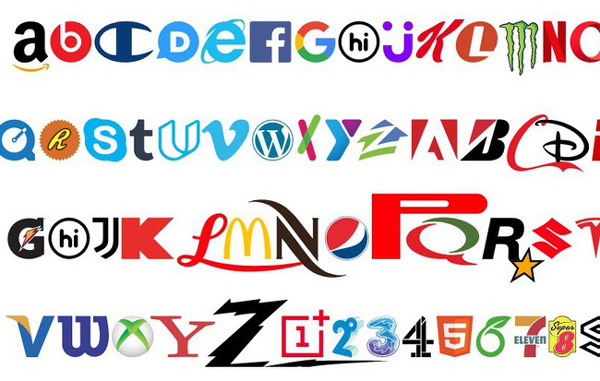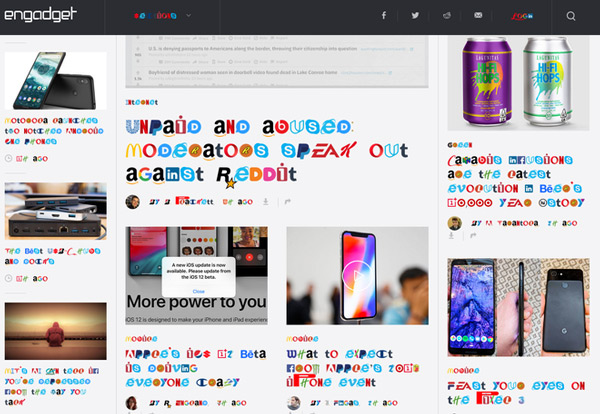
Hello Velocity, một studio đã kết hợp logo của những tập đoàn nổi tiếng trên thế giới để sáng tạo ra một font chữ độc đáo mang tên Brand New Roman. Studio này cho biết, họ tạo ra font chữ mới này nhằm phản ánh Chủ nghĩa trọng tiêu dùng.
Mỗi chữ cái và con số trong font chữ Brand New Roman đều được lấy từ logo của một công ty lớn. Ví dụ như chữ A hoa là logo quen thuộc của Adobe, a thường là Amazon, và số 0 là logo của Target. D là logo của Disney, trong khi d thường là Disqus. R là Rockstar Games, r thường là Reece’s. M hoa lại là hãng thức ăn nhanh McDonald’s và m thường là hãng đồ uống tăng lực Monster. Gõ d hai lần sẽ thành logo của Dunkin’ Donuts, còn khi gõ “hi” sẽ xuất hiện logo của Hello Velocity.
Trang chủ của Engadget sau khi đổi sang font chữ mới.